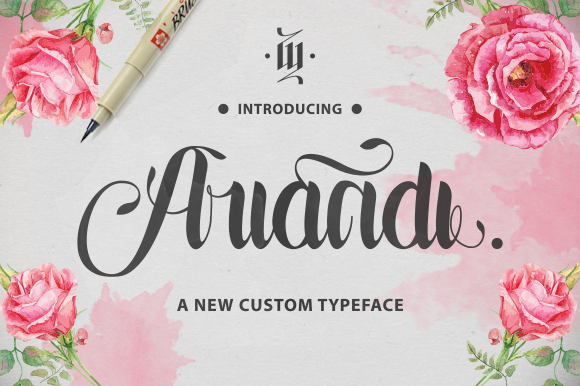
Ariandi Custom Typeface – Download Grátis
Ariandi Custom Typeface é uma tipografia criada para atender a todas as suas necessidades de design, seja para letras efeitos ou logotipos exclusivos. Esta fonte oferece +300 novas formas de caracteres maiúsculas e minúsculas, junto com símbolos de caractere intermediário e final que tornam cada projeto mais único e criativo. Além disso, esta tipografia vem equipada com ornamentos vetorizados adicionais, um verdadeiro presente para quem busca uma fonte personalizada. Instale-a no seu computador ou notebook e comece a criar arte impecável. Ariandi Custom Typeface é perfeita tanto para criação de logotipos quanto para letras efeitos em qualquer projeto gráfico que você possa imaginar.